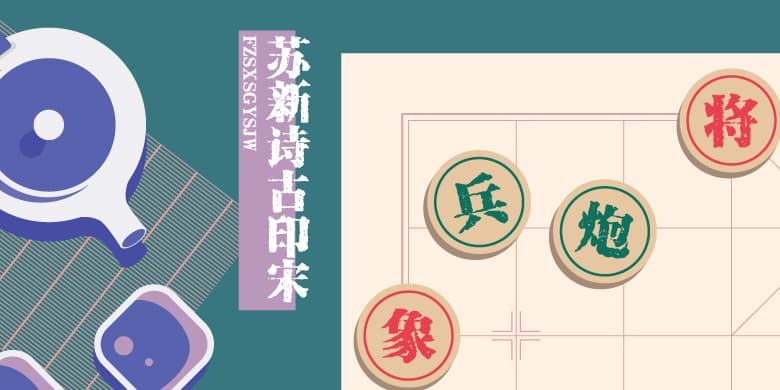
品牌:方正字库设计师:苏新诗发行时间:2019字库编码:大陆简体(GB2312-80)分类:宋体字体属性:精品字
《方正苏新诗古印宋》吸取了古代活版印刷字体的外观特点,并在其基础上进行斑驳仿古处理,是由电脑手写后再调整,从而形成了苏新诗古印宋字体,比较适合广告制作、平面设计、印刷品、书籍封面中使用,增强作品显示效果。